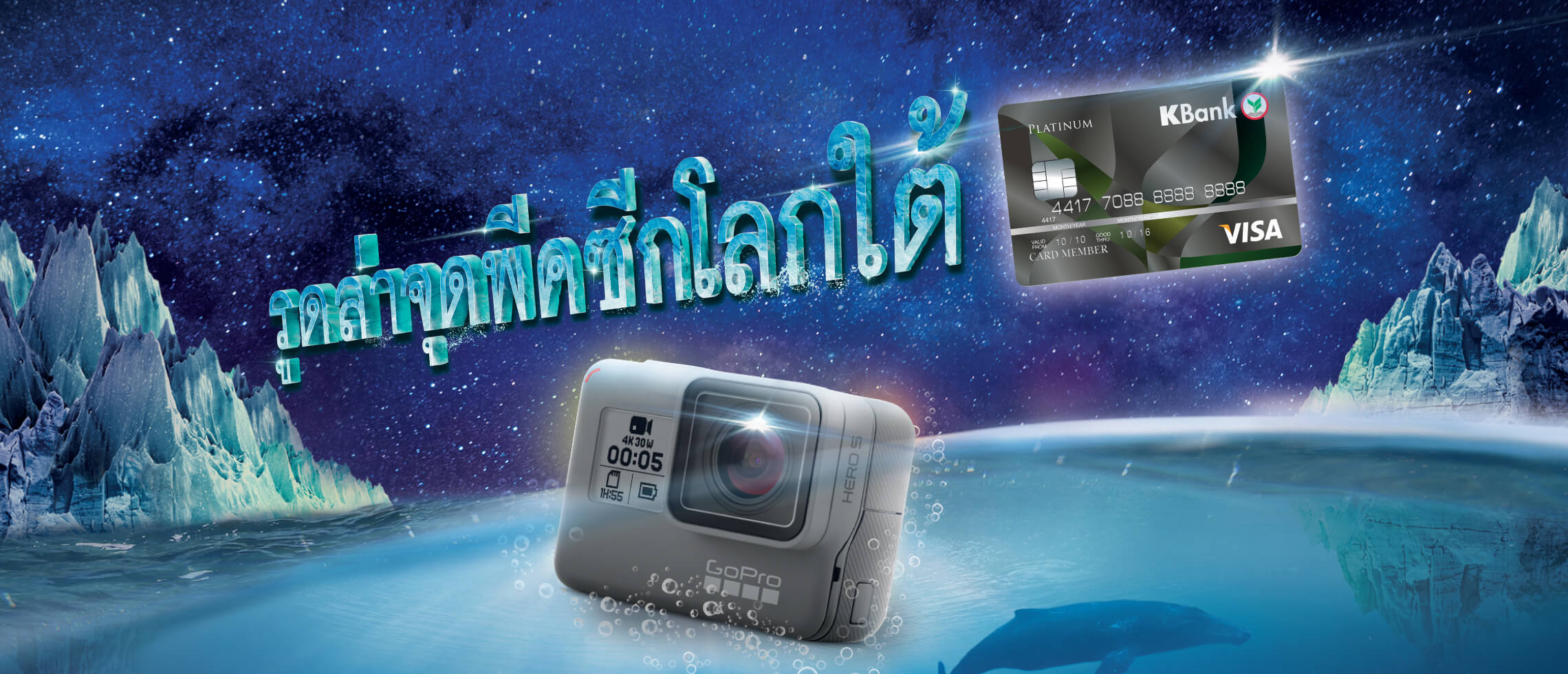
เพราะอยากรู้วิธีทำตัวอักษรแบบนี้มากครับ ใช้โปรแกรมอะไรระหว่าง Ps หรือ Ai ครับ
แสงวิบๆวับๆด้วยนะครับ ปล.หาในยูทูปแล้วครับ ไม่มีแบบนี้เลยครับ
PS ก็ได้นะครับ มี 3D text tool แล้ว
แสง flare นี่หารูปมาแปะเอาทีหลัง แล้วปรับ blending mode ก็ได้ครับ